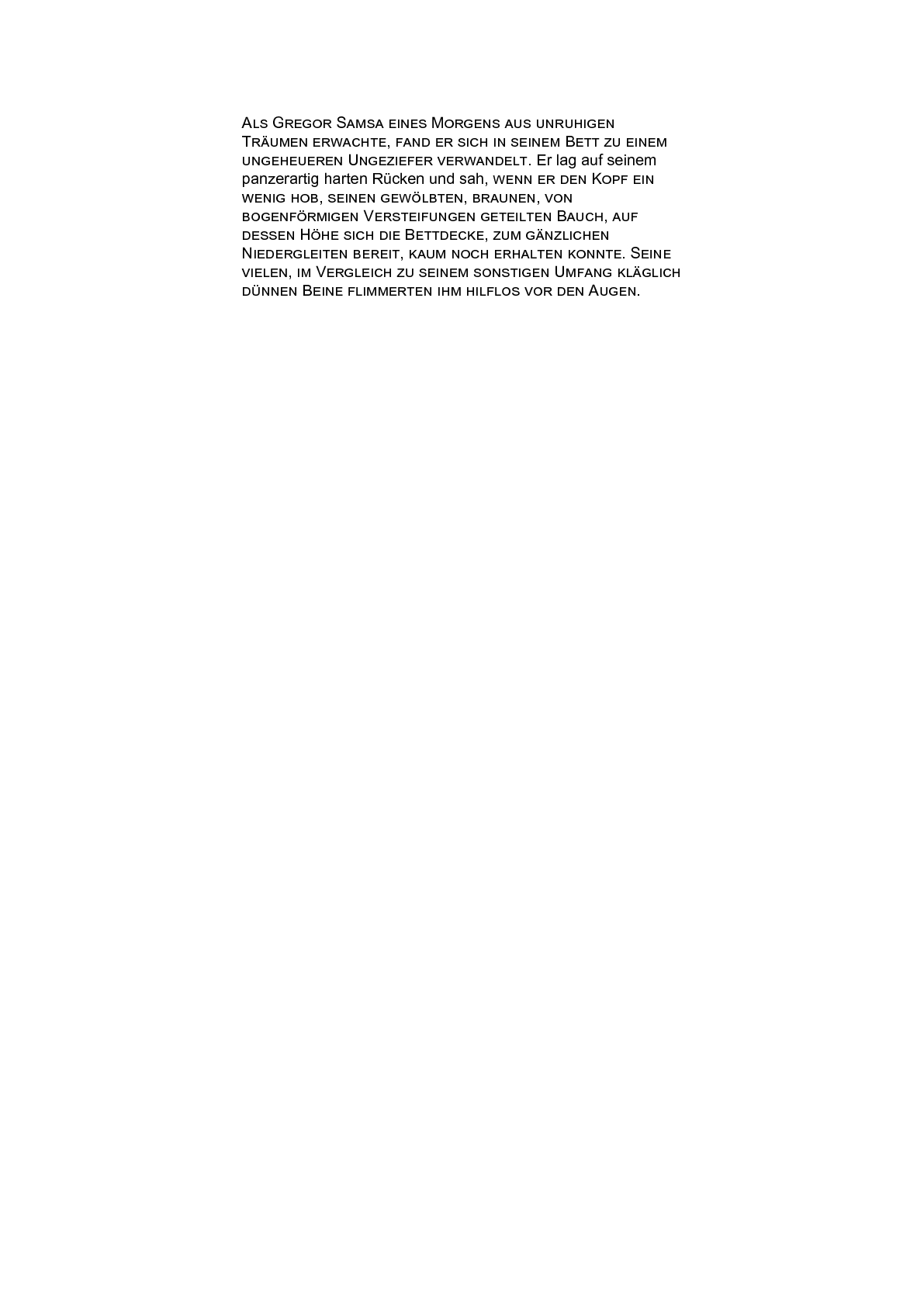
font-variant
Recommendationnummer: 7.9.8
Kategorie: 7.9 Common Font Properties
Beschreibung
Dieses Attribut wird zur Darstellung von Kapitälchen verwendet. Für das lateinische Alphabet vorgesehen, werden Kleinbuchstaben als Großbuchstaben dargestellt, allerdings – um die Unterscheidung zu tatsächlichen Großbuchstaben zu wahren – in der Höhe eines Kleinbuchstabens.
Werte
| normal | Kleinbuchstaben werden mit den dafür vorgesehenen Kleinbuchstaben einer Schrift dargestellt, bzw. die Darstellung durch Kapitälchen wird ausgeschaltet. |
| small-caps | Es werden Kapitälchen zur Darstellung von Kleinbuchstaben verwendet. |
| Vererbt: | ja |
Standardwert: normal
XSL-FO Version: 1.0
Erlaubt in:
<fo:bidi-override> , <fo:block> , <fo:character> , <fo:initial-property-set> , <fo:inline> , <fo:leader> , <fo:page-number-citation> , <fo:page-number-citation-last> , <fo:scaling-value-citation> und <fo:title>Unterstützung:
| Conformance Level | Antenna House | FOP | RenderX XEP | Altsoft XML2PDF | Compart DocBridge |
| Basic | J | N | N | J | N |
XSL-FO Beispiel:
In der Ausgabe: